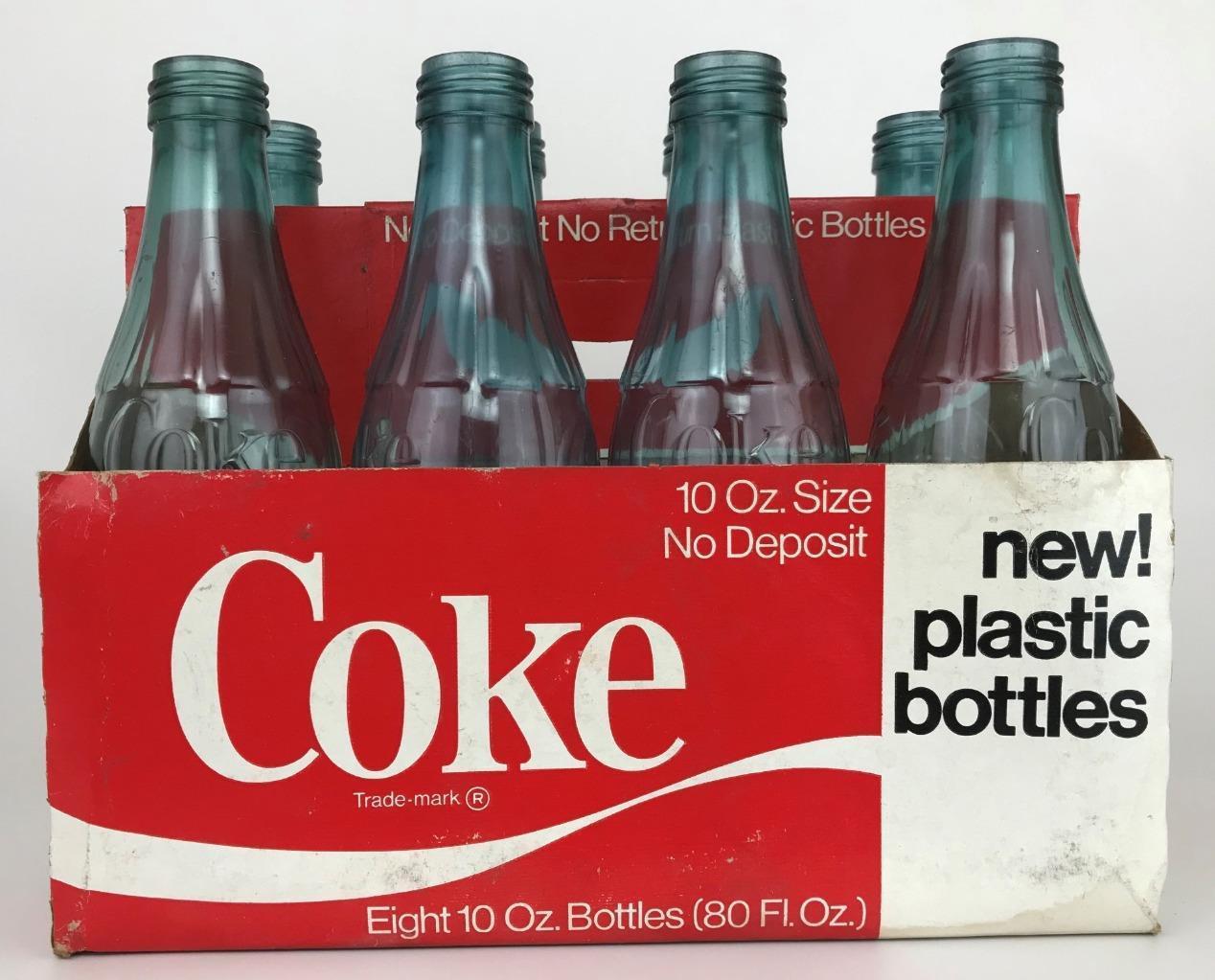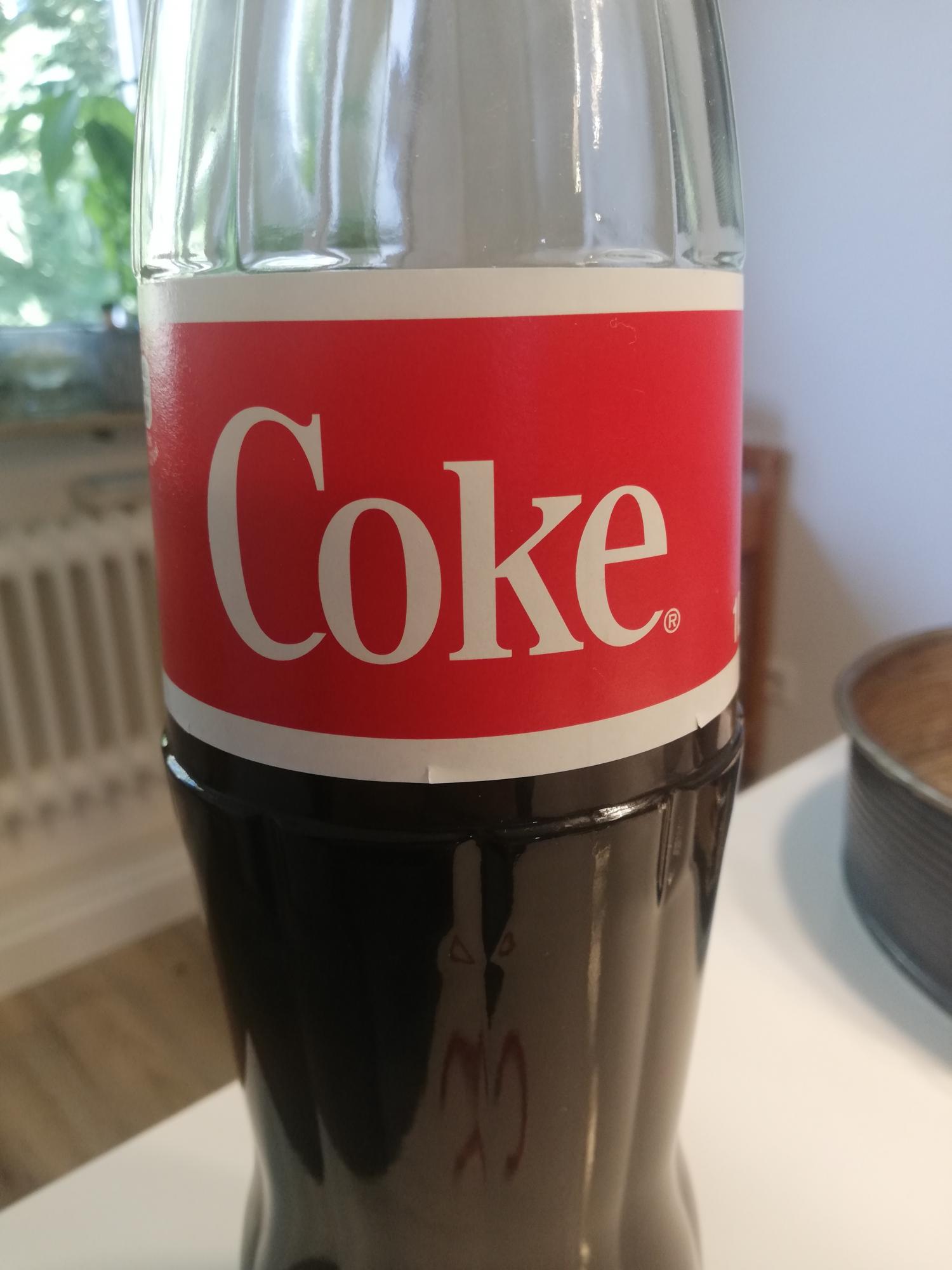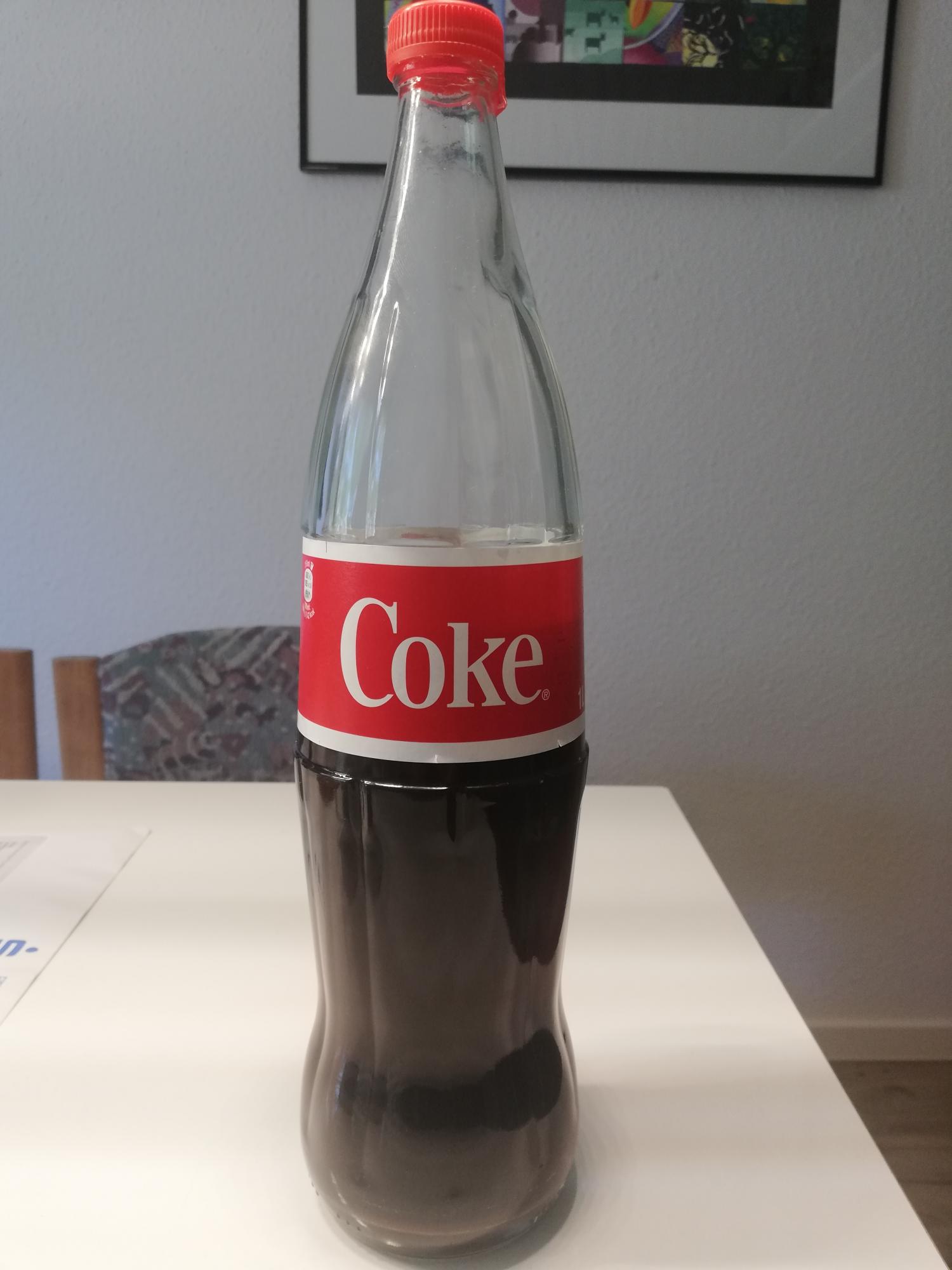
Suche die Schriftart der neuen Retro Coca-Cola
Seit kurzem gibt es von Coca-Cola ein neues Flaschendesign im Einzelhandel. Wo wir in Deutschland normalerweise "Coca-Cola" lesen lautet hierbei die Aufschrift "Coke" und von genau diesem Schriftzug suche ich die Schriftart.
Ich habe euch zwei Fotos meiner neuen Errungenschaft beigefügt.
Als eingetragene Marke wird TCCC kaum eine Satzschrift für das Logo verwendet haben.
Fällt dir eine Schriftart ein, die möglichst nah an die auf der Flasche herankommt?
Die Buchstabenformen können ihrer Verwandschaft mit der TIMES nicht leugnen.
Hier noch ein Foto aus der Zeit, in der der Retro-Schriftzug von heute ganz heißer Scheiß war.